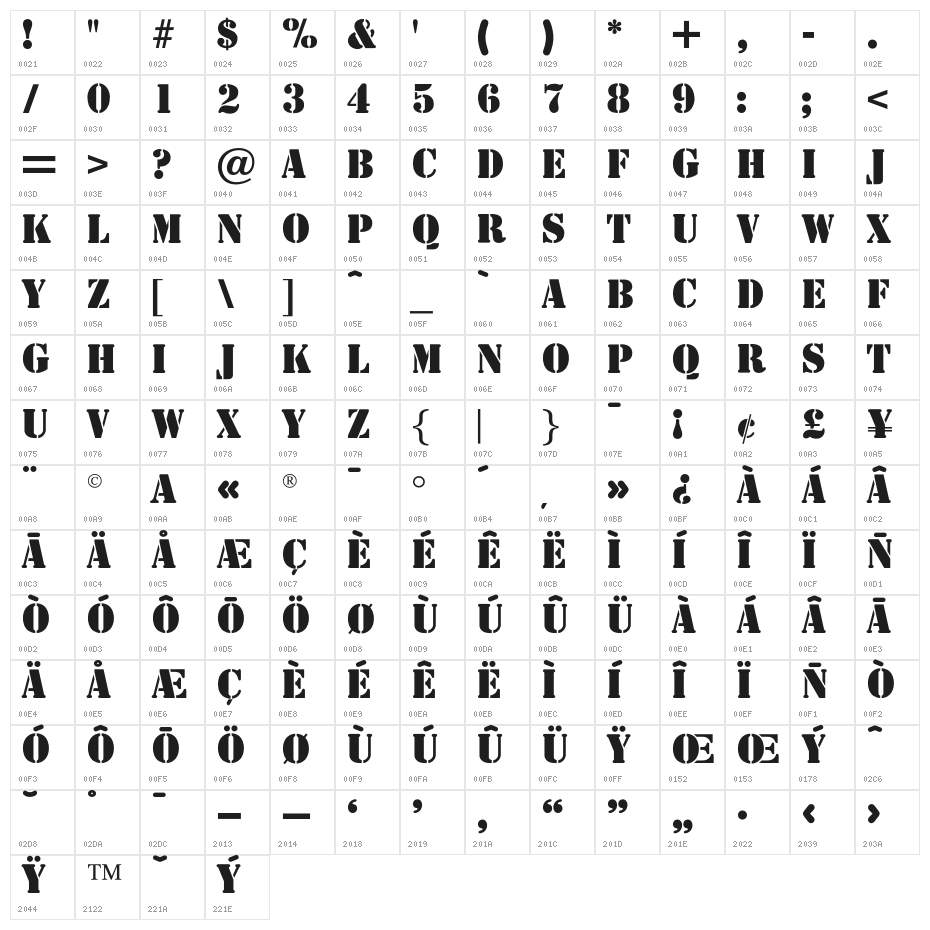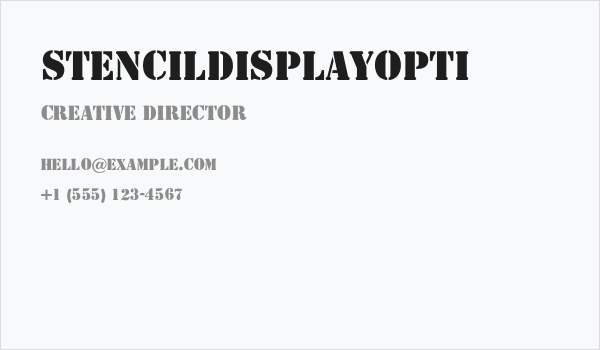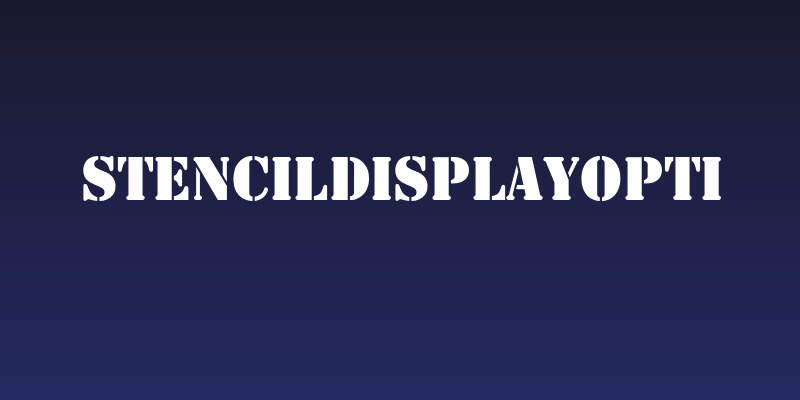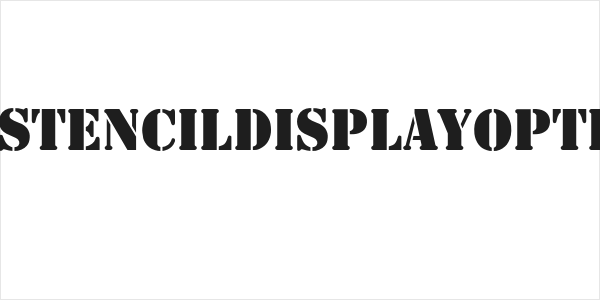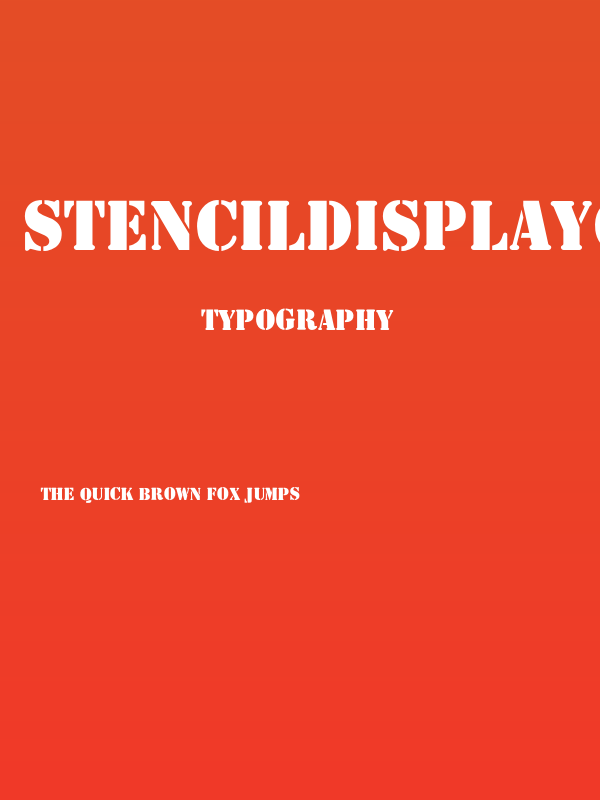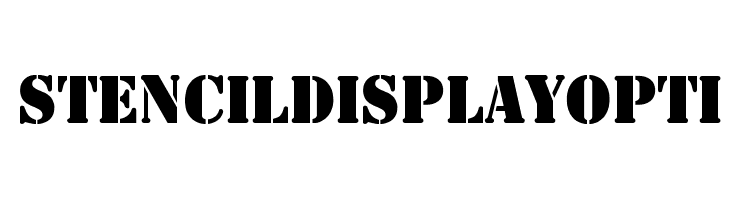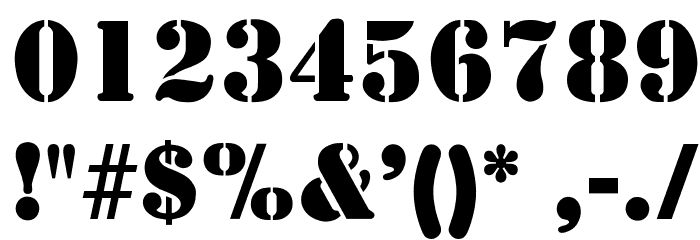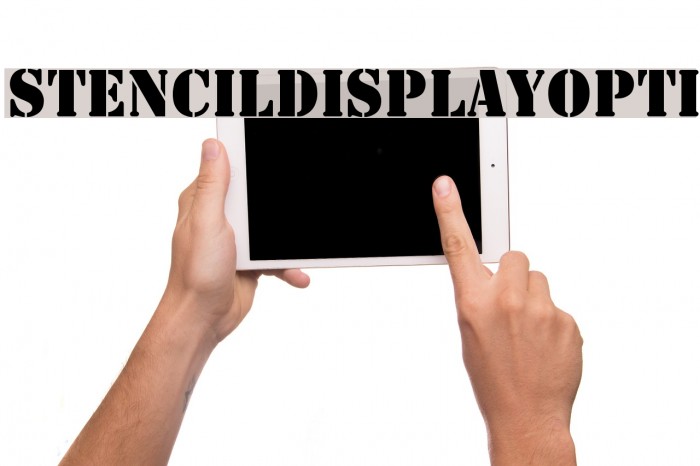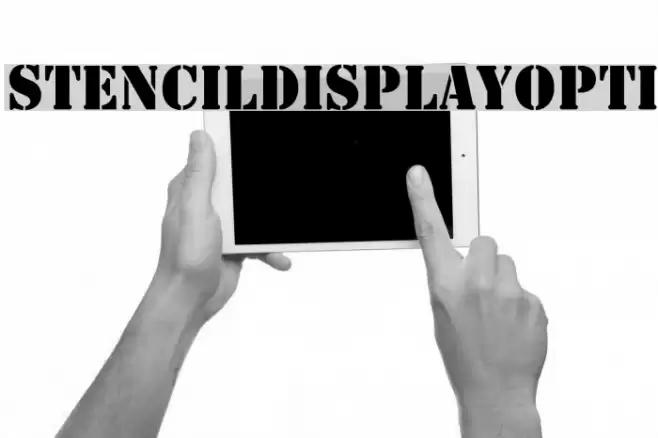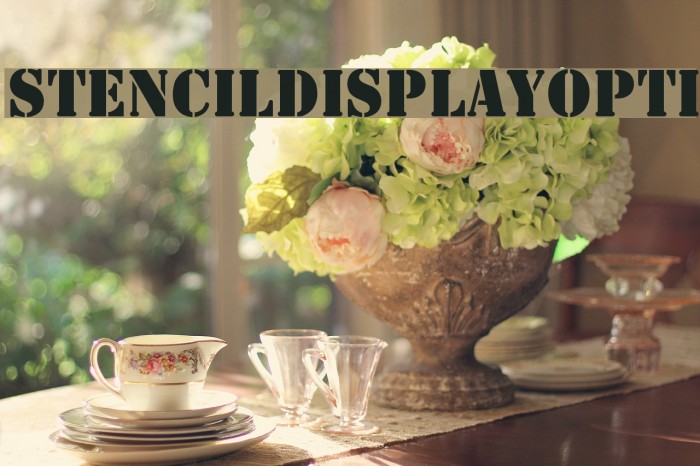
StencilDisplayOpti Font
| Categorii | Stencil |
| Stil general | Industrial, Bold, Rugged |
| Caz de utilizare | Headlines, Posters, Signage |
| Proiecte propuse | Perfect for military-themed designs, industrial signage, posters, and branding that requires a strong, bold statement. |